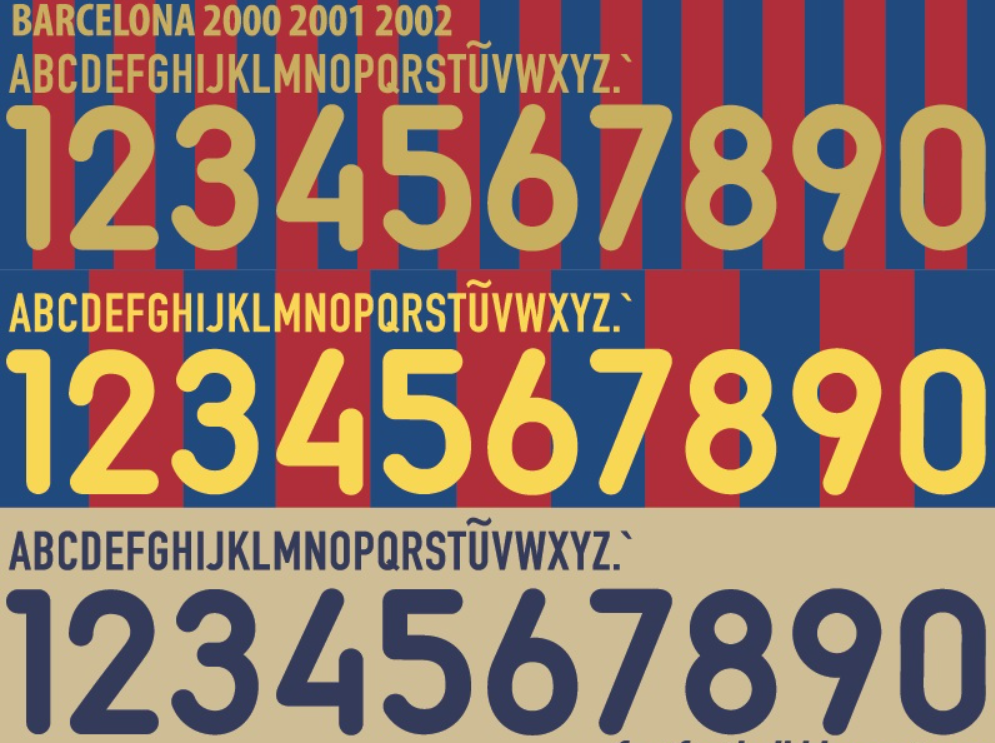
Se você é apaixonado por camisas clássicas, sabe que o início dos anos 2000 marcou uma época inesquecível para o FC Barcelona. Foi o período em que a Nike consolidou sua parceria com o clube catalão, trazendo uniformes que hoje são verdadeiras relíquias de colecionador.
Neste post, trazemos para você o arquivo da fonte utilizada nas temporadas 2000-2001 e 2001-2002. Essa é a tipografia que estampou as costas de lendas como Patrick Kluivert, Pep Guardiola, Luis Enrique e, claro, o nosso craque brasileiro Rivaldo no auge de sua carreira na Europa.
Estilo Visual e Aplicação
A tipografia desenvolvida pela Nike para o Barça nesse período reflete a transição do design dos anos 90 para o novo milênio.
É uma fonte de estilo Block (Blocada), robusta e com serifas sutis e retas, que impõe presença e legibilidade. Diferente das fontes modernas ultra-minimalistas, ela possui uma “alma” clássica. Nos uniformes titulares (Blaugrana), ela era aplicada predominantemente na cor dourada/amarela, criando um contraste perfeito com o azul e grená. Já no uniforme reserva (frequentemente prateado ou dourado naquela época), a fonte assumia tons de azul-marinho ou preto.
É a escolha obrigatória para quem deseja recriar a icônica camisa da temporada em que Rivaldo marcou aquele lendário gol de bicicleta contra o Valencia.